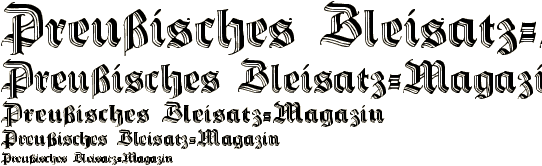
Schaftstiefelgrotesk?
Haha, natürlich stelle ich mir den Reim in der Tannenberg vor, sieht toll aus :lol:
Aus der Tannenberg ist der Spruch für mich nur schwer vorstellbar. Denn er stammt aus der Zeit der Blockade lange vor 1934.
Aber ich möchte Euch wirklich nicht den Spaß verderben.
>Meinst Du alle gebrochene Groteskschriften
Ja! Nach dem Motto "Seit fair zur Schrift".
Wie hieß das noch?
„Gedenke deiner Ahnen.
Sei Deutsch in Wort und Tat.“
Und das aus der Tannenberg.
Warum nicht aus den neuen deutschen Schriften von Spiekermann & Co.?
Das Thema ist hoch aktuell, warum da so eine alte Schrift nehmen.
Heute bekam ich neue Schriften, u.a. die Hermann-Gotisch
Die es auch als digitalen Font gibt:
von Herbert Thannhaeuser aus dem Jahre 1934.
Nein, das ist keine Neue Gotische.
Aber eine interessante Versachlichung der bisherigen Frakuren, wie ich finde. Also folgte sie 1934 durchaus dem Zeitgeist, ohne aber ins martialische abzudriften.
kannst sie ja auch mit einem anderen Text in die Liste Gebrochene Groteskschriften einstellen, eine genaue Abgrenzung ist ja schwierig. Aber passend zum Zeitgeist ja allemal. Ich habe mich jetzt mal für diesen Listentitel entschieden, dann können ja auch Frakturen hinein, wie diese Hermann-Gotisch.
Hinweis zur "Gotika" habe ich schon weiter vorne im Thread gepostet. Die darf nicht fehlen!
Gotika von Imre Reiner
1933 Bauersche Gießerei (Frankfurt a. M.)
Quellen –
Erscheinungsdatum und bei wem:
Digitale Version unter dem Namen "Leather":
Digitalisierung von Manfred Klein auf Moorstation:
Originaldrucke bzw. Scans von Originaldrucken:
Vielleicht kann hier jemand weiterhelfen
Gotika von Imre Reiner
Digitale Version unter dem Namen "Leather":
Digitalisierung von Manfred Klein auf Moorstation:
Manfred Klein hat, soweit ich weiß, nur Zier-Initialen zur Gotika digitalisiert nicht die Schrift selbst.
>Meinst Du alle gebrochene Groteskschriften.
Gebrochenen Groteskschriften
Beispiel:
Gotika (1933)
Imre Reiner <ref>Klingspor Museum: Imre Reiner (http://klingspor-museum.de/KlingsporKue ... Reiner.pdf)</ref>